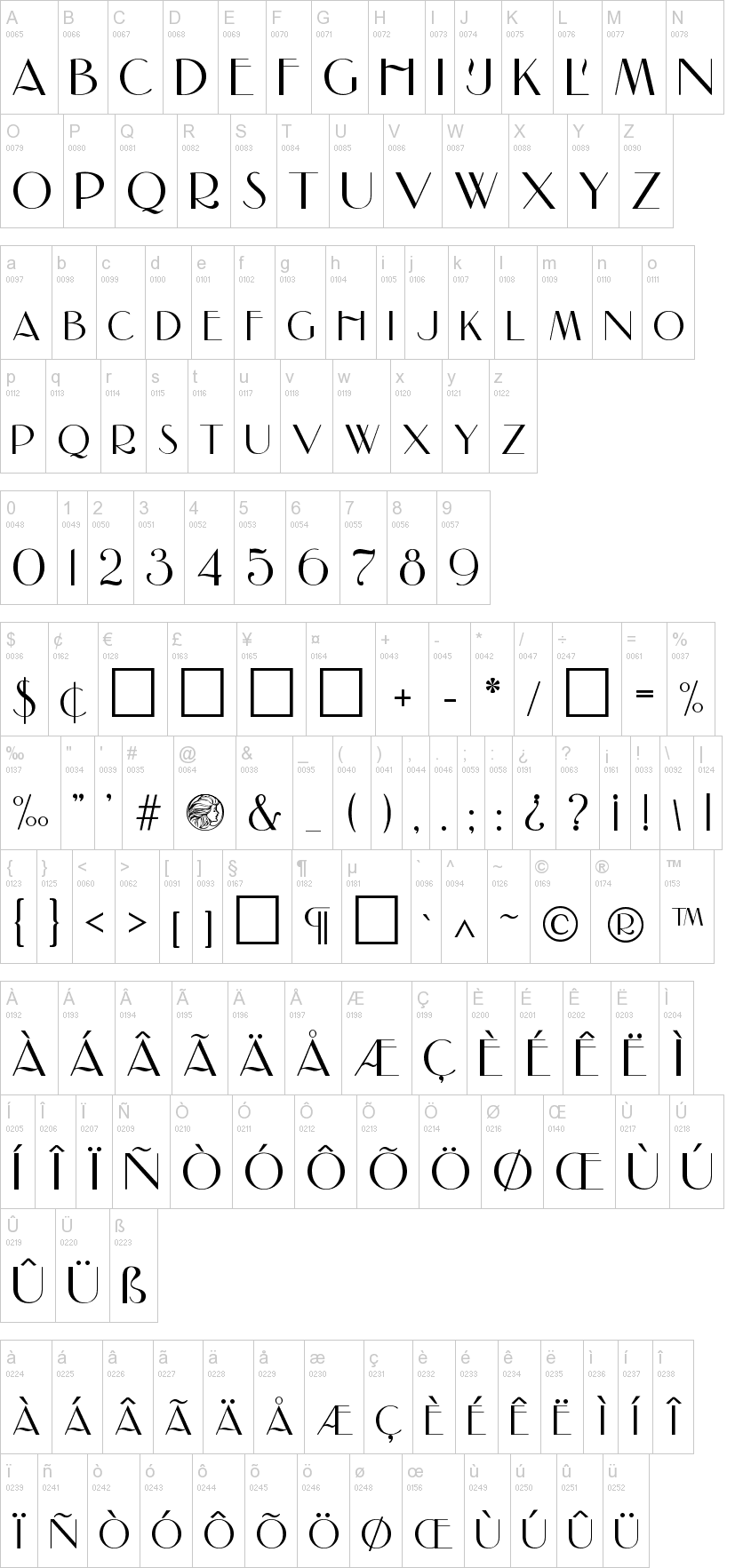
Nadall
Nadall 字体是一种现代化的无衬线字体,它由设计师Jan Charvát于2018年创建。这个字体的设计受到了传统的高对比度衬线字体的影响,但更加简洁和现代化。 Nadall 字体具有优美的曲线和明确的几何外形。它的字母形状简单,容易阅读,适合各种设计用途。此外,它的字母结构还具有一定的均衡感和稳定性,使得这个字体在显示屏上表现良好,也非常适合用于印刷品设计。 总之,Nadall 字体是一种非常出色的现代化无衬线字体,适合各种设计用途,从标志和海报到网站和移动应用程序。
Nadall是一款非常不错的手写艺术字体,具有很好的视觉感,适合于文化类的宣传设计、商业类品牌的广告和产品包装设计以及个性化文字排版等较多场景。